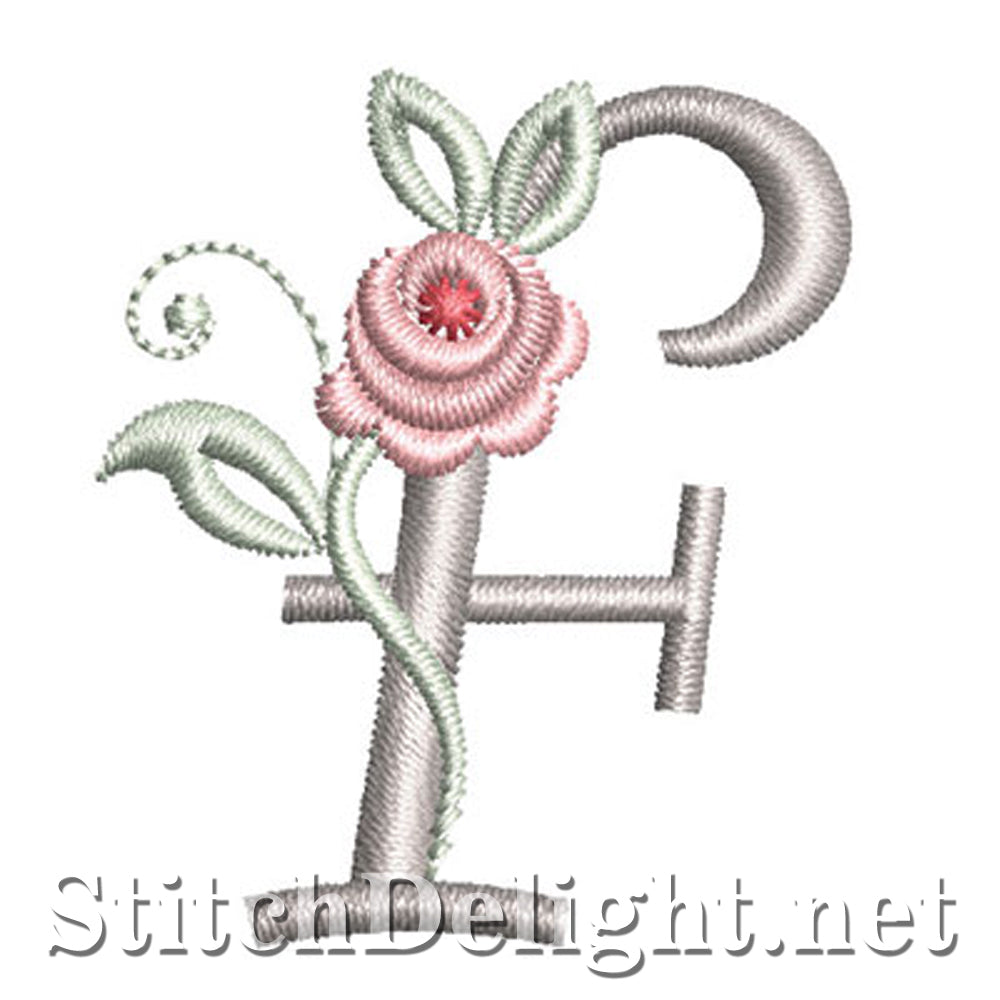
SDS1227 Police Rose Antique F
Personnalisez votre projet avec cet ensemble de monogrammes élégants avec une rose délicate - une superbe couture ton sur ton. Version BX pour le logiciel Embrilliance - La hauteur des lettres est de 1,20 pouce / 30 mm